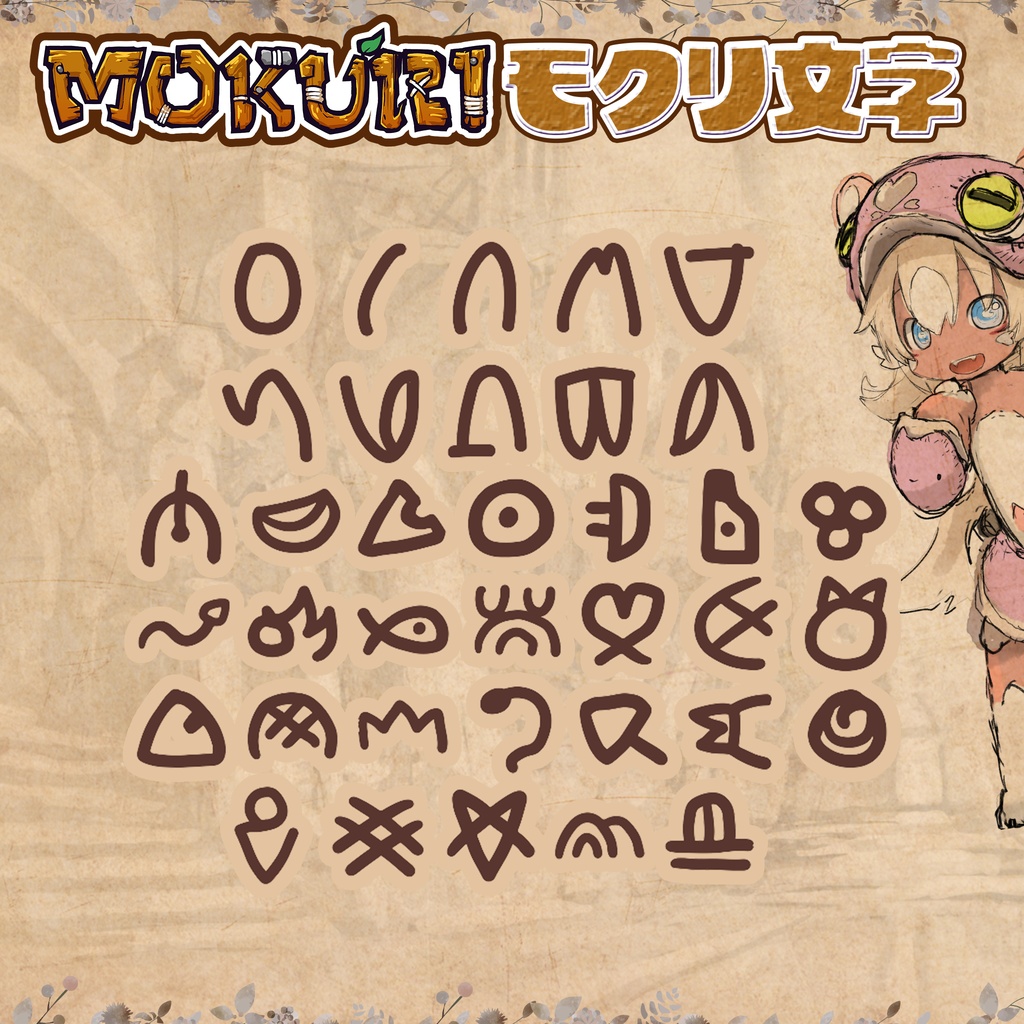
★モクリ文字(mokuri font)★(無料フォント)
こんにちは!モクリプロジェクトです! こちらは「モクリ」の世界で古くから使われるている文字です! 私たちが観測している文字はこれだけですが、もしかしたらもっと別の場所では違う文字として発展してるのかもしれません・・・。 無料のフォントです!是非沢山のモクリ族、開拓者、色々な方に使っていただきたいです! もちろん使用の際は利用規約をご一読くださいね! ◆「MOKURI project」とは? VR空間のキャラクター「モクリ」を中心としたキャラクタープロジェクトとして発足しました。創作コミュニティ×自由な二次創作活動の保護による、新しいモデルでの作品成長に挑戦していきます。2020年4月26日には【アニメ】『MOKURI(モクリ)』ショートフィルムを公開しました。「バーチャルマーケット」では、不定期に「モクリの世界」のワールドを制作・公開しています。それらの展開に合わせつつ、モクリ文字から様々な種族のアバターまで幅広く展開しています。一人でも多くの「モクリファン」に自由な発想で「モクリの世界」を広げていっていただきたいと願っております。改変レッサーモクリをはじめとした各所属アバターの改変など、VR空間やSNSで沢山発信していってください!一緒に「モクリの世界」を遊びつくしましょう! 【MOKURI project】 公式HP<http://mokuri.world/> 公式Twitter<https://twitter.com/mokuriproject>